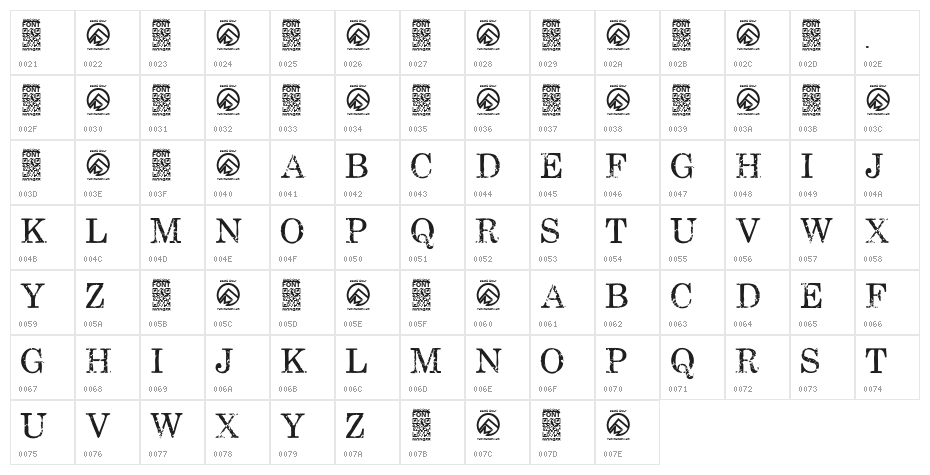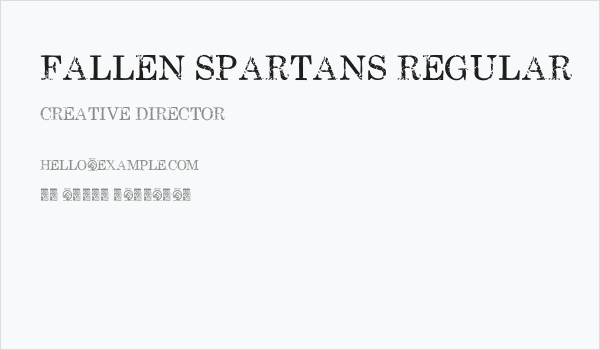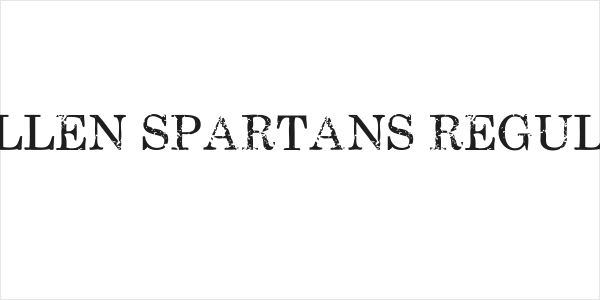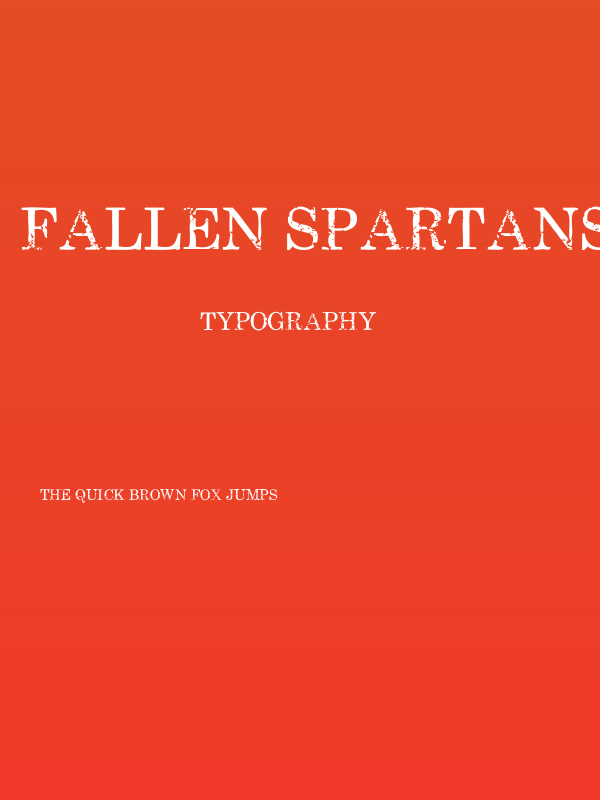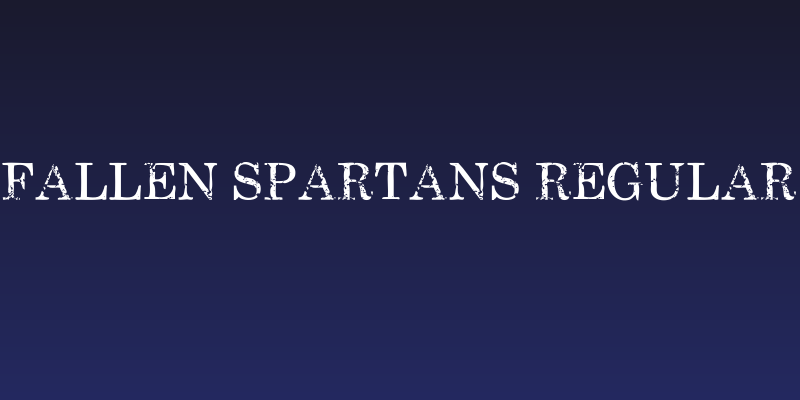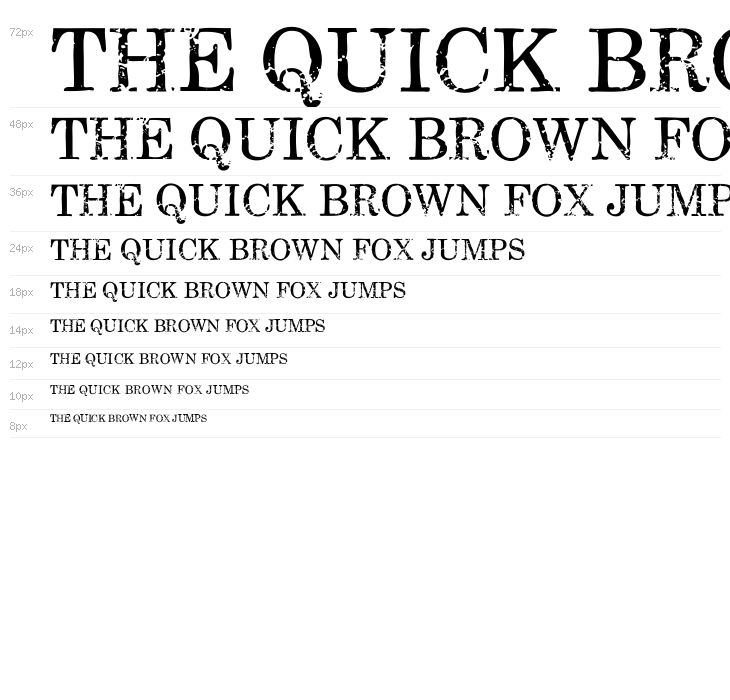
Fallen Spartans Regular Font
✎ Messy
| Vorgeschlagene Projekte | Ideal for use in posters, video game titles, movie titles, and branding for products that emphasize strength and durability. |